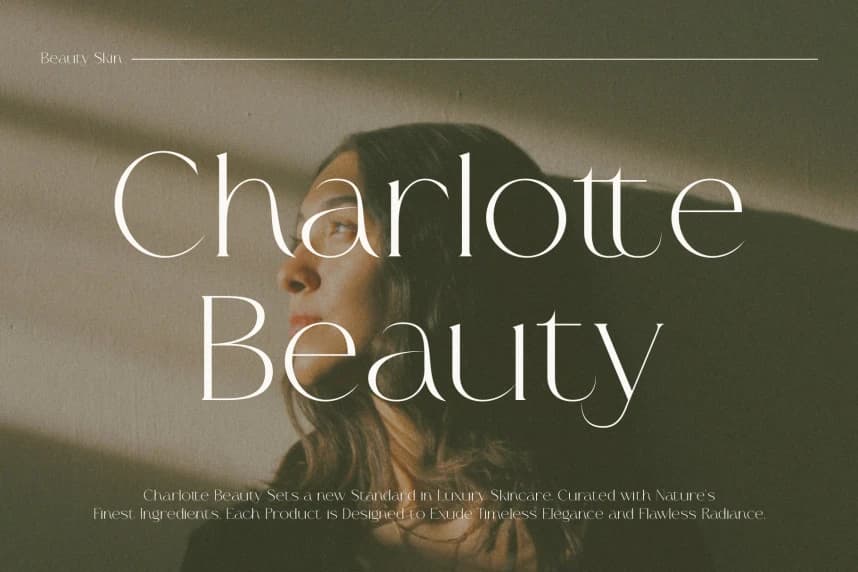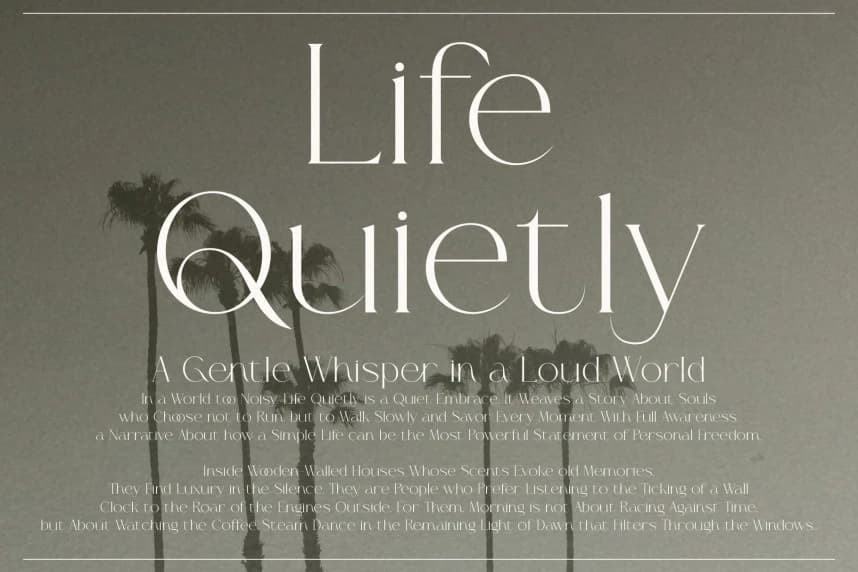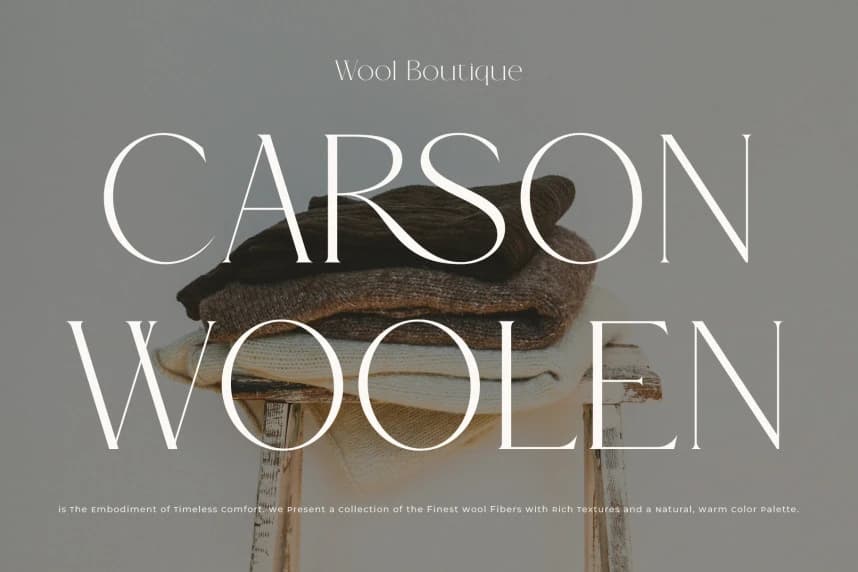
The Genium Font
The Genium Font, saygın ve şiirsel bir ruha sahip olan yüksek moda gösterişli bir serif fontudur. Bu font, arşivsel Roma mükemmeliyetini modern editoryal ile köprüleyen ritmik, akıcı eğriler ve jilet gibi keskin uçlar tarafından benzersiz biçimde tanımlanan çarpıcı, yüksek kontrastlı harf biçimlerin
Genium Font, prestijli ve şiirsel bir ruha sahip olan yüksek moda gösterişli bir serif yazı tipidir. Bu yazı tipi, çarpıcı, yüksek kontrastlı harf biçimlerine sahiptir ve ritmik, akıcı eğriler ile keskin uçlar tarafından benzersiz biçimde karakterize edilmiştir; arşiv Roma mükemmeliyeti ile modern editoryal markalaşma arasındaki uçurumu köprüler.